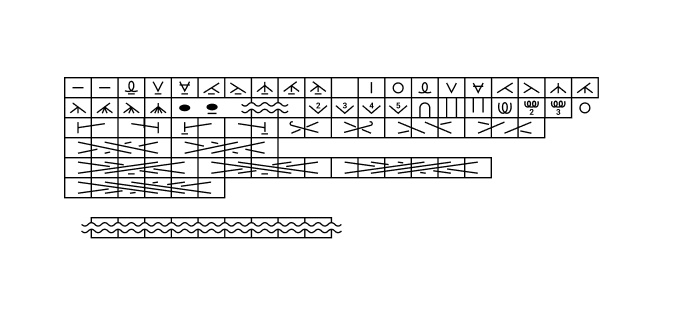
棒針編み用・編み図記号フォント(ベータ版)
文字を打つだけで編み図が簡単につくれる棒針編み用の編み図記号フォントを作成しました。 【概要】 - 記号だけでなく周りの四角の枠も含んだ等幅のフォントになっていて、テキストを打つだけで編み図を作成する事が可能です(数字や矢印は別途入れないといけないですが...) - 棒編みの記号のみ対応しています - こちらで使える記号一覧を見る事が可能です https://www.figma.com/file/GLcx2llMP4X711jepfGWJt/Amis-font-preview - 文字と記号の対応表を作っておらず、代わりに以下の文字を編み図記号フォントを適用したテキストエリアにコピペすると、使える文字を全て表示する事ができます。そこからコピペして使用いただけますと... ``` abdefghijklmn BDEFGHIJKꀉ ꀀꀁcꀅꀆꀇꀈꀒꀓꀔꀐ ꈀꈁ ꀑ ꈂꈃ ꈄꈅ ꌀꌁ ꐀꐁꔀꔁꘀꘁ ꀂꀃꀃꀃꀃꀃꀃꀃꀃꀃꀄ ``` - 予告無しでデータのアップデート、販売の中止、値段変更等を行う場合があります - 今後アップデートとして、足りない文字などを追加する予定です - 追加の過程で記号に割り当てられた文字コードが変更になる場合があります - 修正が一旦落ち着いたら完成版としてリリースします - ベータ版として無料で公開していますが、正式版のリリース後に価格を変更する可能性があります - Adobe IllustratorやPhotoshop、Figma、Sketchなど、フォントが指定できるあらゆるデザインソフトで使用可能です - ご感想、ご要望等ございましたら https://docs.google.com/forms/d/e/1FAIpQLSfAMJI8LX-oZ_ku6rh3aMXwowAD11-ors5f92KDORgWcVGUmQ/viewform からご連絡ください 【利用規約】 - 商用利用可能 - クレジット表記不要 - 再配布禁止 - 著作権は放棄していません - 当データを使用していかなる損害が発生したとしても当ショップでは責任を負いません